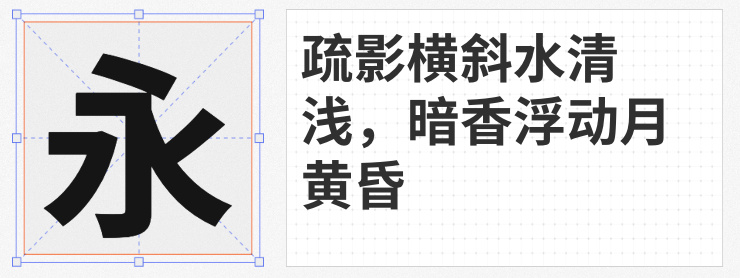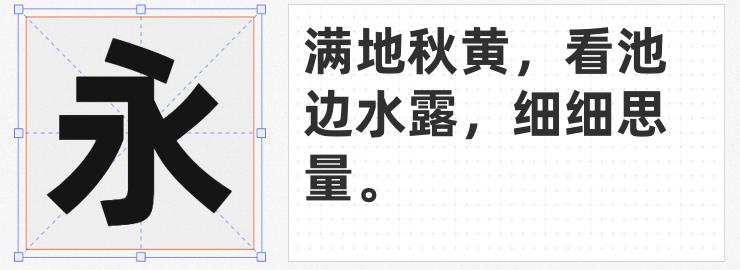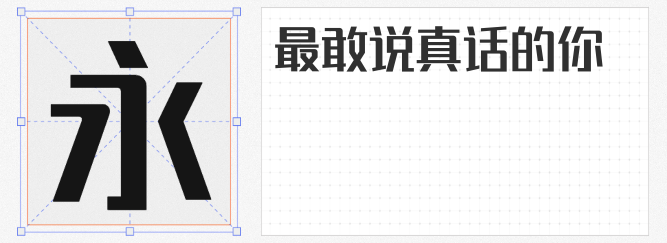
在商业海报设计中,字体不仅是信息载体,更是品牌调性与视觉张力的核心表达。本文精选四款免费可商用的中文字体,从设计风格到应用场景,为设计师提供高效且专业的解决方案。
锐字潮牌真言简2.0免费 准粗以“直角与圆角错落搭配”打破传统黑体的刻板印象。其笔触浑厚如刀刻,转折处却以圆角收尾,形成“刚柔并济”的视觉张力。该字体可强化力量感,而圆角细节又能避免生硬,适配年轻化、潮流化的设计需求。
由Adobe与Google联合开发的思源黑体,以“泛CJK字体家族”定位覆盖中日韩等多语言场景。其Bold字重(字重类型700)笔画粗细均匀,结构严谨,适合需要高辨识度的标题设计。
专为商业场景打造的阿里巴巴普惠体,以“20岁少年的精气神”为设计理念。其95 ExtraBold字重(字重类型800)通过提高重心、省略标题字出脚,形成瘦长且简洁的视觉效果。在电商促销海报中,该字体可突出价格标签的醒目性;而中文字符29194个、西文7205个的庞大字符集,更支持多语言排版需求。
作为阿里妈妈营销字体的代表作,数黑体以“图形感与书写感的平衡”为核心。其字型饱满如黑体,但笔画末端微调的弧度又赋予书写温度,在海报设计中,既能传递产品的高端感,又通过圆润细节拉近与消费者的距离。
设计师可根据品牌调性、场景需求与传播目标,灵活组合使用,让每一份海报都成为精准的视觉表达。